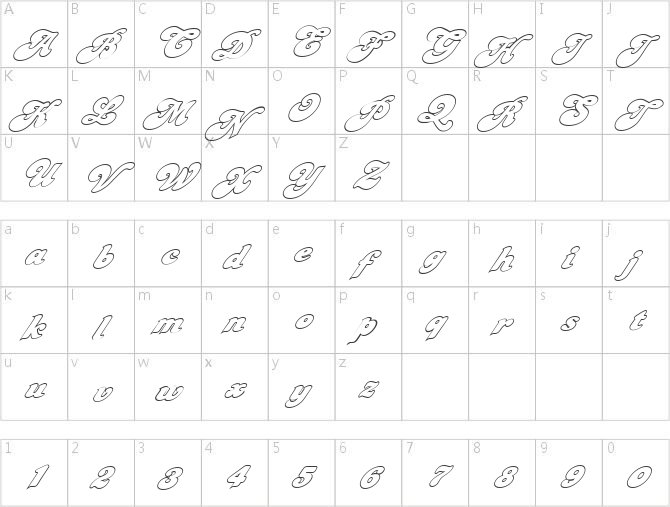
FZ JAZZY 49 HOLLOW ITALIC 詳情頁
FZ JAZZY 49 HOLLOW ITALIC字體字庫是一款讓人賞心悅目、百看不厭的英文字體,適合各類廣告和產(chǎn)品包裝設(shè)計(jì)應(yīng)用,字體大小0.12MB,格式為ttf字體,上傳用戶是素年錦時(shí),作者/版權(quán)方為未知